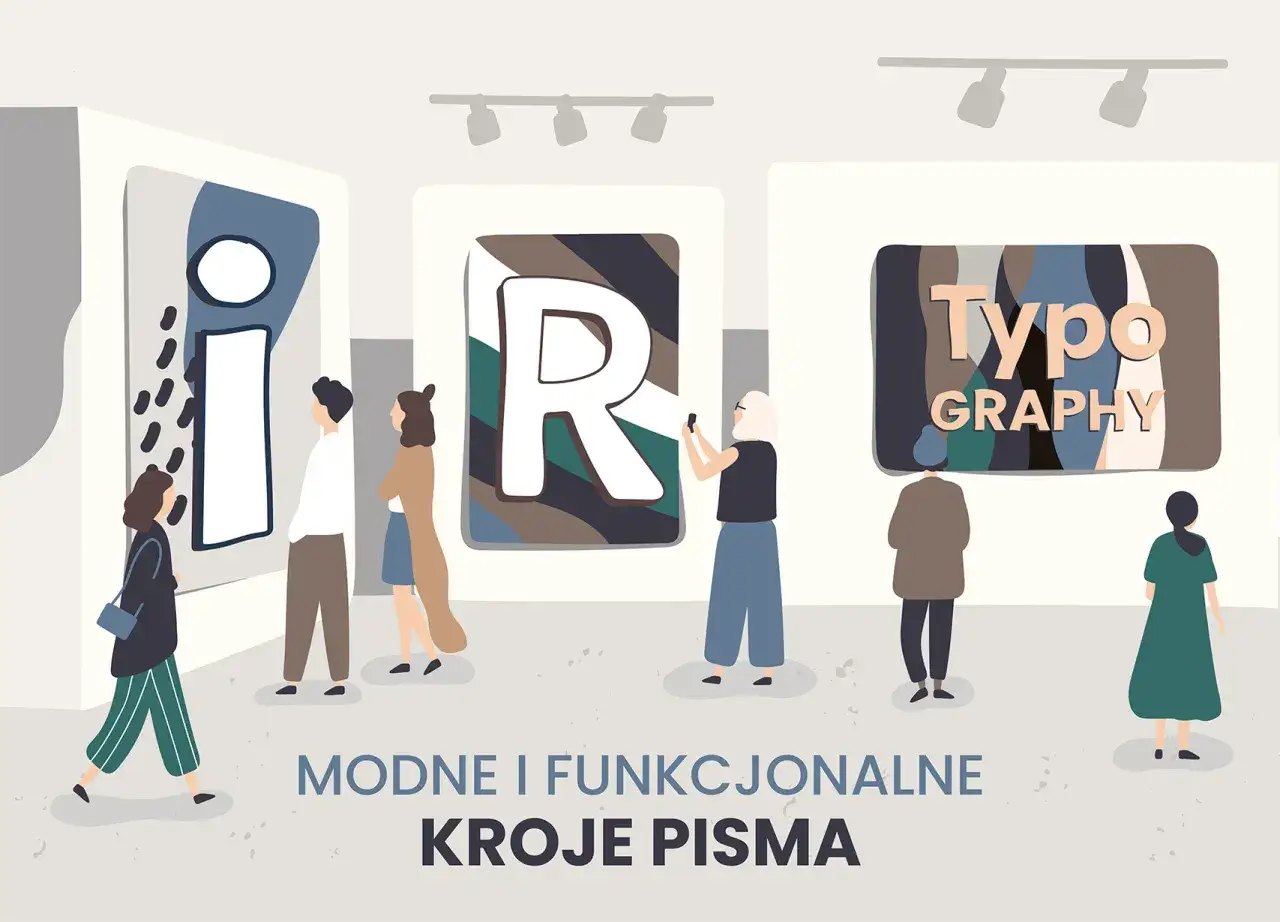
Dziwne czcionki w praktyce. Jak używać ich z wyczuciem
Porównanie zużycia tuszu przez czcionki: Times New Roman, Garamond, Courier, Ryman Eco, bezszeryfowe i szeryfowe. Niektóre dziwne czcionki zużywają mniej tuszu.
Dziwne czcionki potrafią natychmiast nadać projektowi charakter, ale łatwo zamienić ciekawy pomysł w typograficzny chaos. Wyjaśniam, czym różnią się nietypowe kroje pisma od ozdobnych znaków kopiowanych z generatorów, pokazuję ich rodzaje i podpowiadam, jak używać ich w plakatach, logotypach, ilustracjach oraz mediach społecznościowych.
Nietypowy krój działa najlepiej wtedy, gdy wspiera treść
• Eksperymentalne liternictwo może być ozdobą, ilustracją albo głównym tematem kompozycji.
• Jedna wyrazista czcionka zwykle wystarczy, aby nadać projektowi indywidualny styl.
• Znaki Unicode udające fonty nie są prawdziwą czcionką i mogą nie wyświetlać się poprawnie.
• Czytelność ma pierwszeństwo przed efektem, szczególnie w dłuższym tekście i małych rozmiarach.
• Licencja fontu decyduje o tym, czy można użyć go w logo, publikacji albo projekcie komercyjnym.
Wystawa prezentuje nowoczesne, dziwne czcionki i litery, takie jak
Co właściwie kryje się pod określeniem dziwne czcionki
To określenie jest bardzo pojemne. Może oznaczać font z literami przypominającymi bazgroły, krój gotycki, napis złożony z roślin, cyfrowe glitche albo znaki wyglądające jak symbole z obcego alfabetu. W typografii częściej mówi się o krojach ekspresyjnych, dekoracyjnych, eksperymentalnych lub displayowych, czyli przeznaczonych przede wszystkim do krótkich, mocno eksponowanych tekstów.
Trzeba też rozdzielić dwie rzeczy, które w internecie często wrzuca się do jednego worka. Prawdziwy font jest plikiem zawierającym zaprojektowany zestaw znaków, odstępów i reguł ich łączenia. Generator ozdobnych napisów najczęściej podmienia zwykłe litery na znaki Unicode, które tylko przypominają inną czcionkę. Taki napis można wkleić do profilu, ale nie daje on pełnej kontroli typograficznej.
Intencja stojąca za tym tematem jest zwykle mieszana. Część osób szuka szybkiego sposobu na oryginalny nick lub podpis, a część inspiracji do plakatu, tatuażu, okładki czy identyfikacji wizualnej. Dla mnie ta druga grupa jest ciekawsza, bo nietypowe litery najlepiej pokazują swoje możliwości wtedy, gdy stają się elementem obrazu, a nie tylko ozdobą tekstu.
Rodzaje nietypowych krojów i ich charakter
Najłatwiej wybrać odpowiedni styl, gdy najpierw określi się emocję, którą ma wywołać napis. Inaczej działa ciężka fraktura, inaczej delikatne pismo odręczne, a jeszcze inaczej litery celowo zdeformowane przez projektanta.
Rodzaj Jak wygląda Gdzie sprawdza się najlepiej Główne ograniczenie
Blackletter i gotyk Ostre, gęste, historyzujące formy Plakaty koncertowe, okładki, tatuaże, projekty inspirowane średniowieczem Mała czytelność w dłuższych tekstach
Odręczne i brush lettering Nierówne, dynamiczne, przypominające pismo ręczne Zaproszenia, opakowania, plakaty artystyczne, posty lifestyle Trudniejsze dopasowanie liter i polskich znaków
Glitch i dekonstrukcja Przerwane, przesunięte lub „uszkodzone” znaki Muzyka elektroniczna, sztuka cyfrowa, gaming, moda Szybko traci czytelność w małym rozmiarze
Fonty organiczne Litery zbudowane z liści, kości, włókien lub płynnych kształtów Ilustracja, plakaty ekologiczne, fantasy, projekty edukacyjne Najczęściej działają tylko jako pojedynczy napis
Geometryczne i modularne Litery złożone z powtarzalnych modułów Logotypy, infografiki, okładki i identyfikacje marek Potrzebują konsekwentnego systemu odstępów
Ozdobne znaki Unicode Tekst przypominający kursywę, frakturę, bąbelki lub maszynopis Nicki, krótkie bio, podpisy i komunikacja w mediach społecznościowych Różna obsługa znaków na urządzeniach
W praktyce najbardziej efektowne kroje są często najmniej uniwersalne. Font z literą przypominającą pajęczynę może świetnie zadziałać w tytule plakatu, ale po zmniejszeniu do 14 pikseli stanie się plamą. Zawsze testuję napis w docelowym rozmiarze i na docelowym tle, bo podgląd w dużym arkuszu projektowym bywa mylący.
Jak dobrać styl do projektu, a nie tylko do własnego gustu
Najpierw pytam, co odbiorca ma poczuć i zapamiętać. Jeśli projekt dotyczy wystawy o dawnych technikach, gotyk lub krój inspirowany pismem rękopiśmiennym może budować wiarygodny klimat. Przy plakacie o sztuce cyfrowej lepiej sprawdzą się deformacje, pikselowe przerwy albo litery o zmiennym rytmie.
Pomaga prosta zasada funkcji. Tekst informacyjny powinien być spokojniejszy, a nietypowy krój może przejąć rolę nagłówka, podpisu lub znaku rozpoznawczego. Gdy cała strona jest złożona z ozdobnych liter, odbiorca nie wie, co jest najważniejsze i męczy wzrok jeszcze przed przeczytaniem treści.
Trzy pytania przed wyborem fontu
• Czy napis ma być przeczytany w sekundę, czy oglądany jak ilustracja?
• Czy będzie używany tylko raz, czy w całym systemie wizualnym?
• Czy potrzebuję polskich znaków, cyfr, znaków interpunkcyjnych i kilku grubości?
Ostatnie pytanie często przesądza o wyborze. Wiele darmowych fontów wygląda interesująco w alfabecie angielskim, ale nie ma poprawnie zaprojektowanych znaków ą, ć, ę, ł, ń, ó, ś, ź i ż. Zamiast ratować taki krój przypadkowymi zamiennikami, wolę znaleźć font z pełnym zestawem znaków dla języka polskiego.
Gdzie można wykorzystać osobliwe litery
Największy potencjał mają krótkie formy, w których litera może pracować podobnie jak ilustracja. Tytuł wystawy, nazwa serii grafik, okładka zinowego magazynu czy napis na opakowaniu dają projektantowi przestrzeń na eksperyment. W takich realizacjach dopuszczam nawet częściową utratę czytelności, jeśli forma świadomie dopowiada znaczenie.
Plakat i okładka
Na plakacie można rozciągnąć słowo, rozbić je na warstwy, obrócić pojedyncze znaki albo potraktować litery jako fakturę. Dobrym ćwiczeniem jest przygotowanie trzech wersji tego samego hasła: spokojnej, agresywnej i całkowicie abstrakcyjnej. Dopiero porównanie wariantów pokazuje, czy efekt wynika z pomysłu, czy wyłącznie z dekoracyjnego fontu.
Logo i identyfikacja wizualna
W logotypie nietypowa litera może stać się znakiem rozpoznawczym, ale nie powinna utrudniać zapisania nazwy z pamięci. Zanim użyję gotowego kroju, sprawdzam możliwość modyfikacji wybranych znaków, odstępy między literami i wygląd wersji czarno-białej. Logo musi działać zarówno na dużym plakacie, jak i w rozmiarze około 24-32 pikseli w interfejsie cyfrowym.
Media społecznościowe
Do krótkiego bio lub nazwy profilu można użyć znaków Unicode, ponieważ nie wymagają instalowania pliku fontu. To rozwiązanie ma jednak sens głównie dla kilku słów. Przy dłuższych opisach, polskich znakach i ważnych informacjach wybieram zwykły tekst, bo kompatybilność jest ważniejsza od chwilowego efektu.
Liternictwo tworzone ręcznie
Najciekawsze rezultaty często powstają poza biblioteką fontów. Można narysować litery ołówkiem, pędzlem, markerem lub tabletem, a potem zeskanować je i opracować cyfrowo. Taka metoda daje nierówności, których nie da się wiarygodnie udawać gotowym krojem, i pozwala dopasować napis do konkretnej ilustracji.
Prawdziwy font czy ozdobny tekst do skopiowania
Jeżeli potrzebuję jednego krótkiego podpisu w profilu, generator Unicode jest szybki i wygodny. Wpisuję tekst, wybieram wariant, kopiuję go i sprawdzam na telefonie oraz komputerze. Nie traktuję jednak takiego rozwiązania jako zamiennika fontu w programie graficznym.
Kryterium Font zainstalowany w programie Tekst Unicode
Kontrola wyglądu Duża, można zmieniać rozmiar, kerning i układ Ograniczona do dostępnych znaków
Polskie znaki Zależne od zakresu fontu Często problematyczne
Skalowanie Dobre w projekcie wektorowym Zależy od aplikacji i urządzenia
Zastosowanie Druk, logo, grafika, strona internetowa Krótki podpis, nick, bio, wiadomość
Ryzyko Błędna licencja lub brak potrzebnych znaków Puste kwadraty, zastępcze symbole, problemy z czytnikami ekranu
Najczęstszy błąd polega na tym, że ozdobny zapis trafia do nazwy wydarzenia, daty albo adresu. Jeśli część odbiorców zobaczy w tym miejscu kwadraty lub niezrozumiałe symbole, projekt przestaje spełniać swoją funkcję. W przypadku ważnych komunikatów lepiej użyć prawdziwego fontu i dekoracyjny styl ograniczyć do grafiki.
Przy każdym pliku sprawdzam też licencję. Informacja „darmowy” nie zawsze oznacza możliwość użycia w reklamie, logo lub produkcie sprzedawanym komercyjnie. Licencja, zakres znaków i format pliku są równie ważne jak sam wygląd liter.
Jak eksperymentować, żeby nie stracić czytelności
Dobry projekt typograficzny potrzebuje kontrastu. Jeśli nagłówek jest bardzo dekoracyjny, tekst pomocniczy powinien być prosty, najlepiej w kroju bezszeryfowym o regularnym rytmie. Zwykle ograniczam zestaw do jednego fontu ekspresyjnego i jednego neutralnego, a różnicę buduję wielkością, grubością oraz odstępami.
W tekście ciągłym sprawdzają się kroje, w których litery mają wyraźne kształty i równy kolor optyczny. Na ekranie zaczynam od rozmiaru około 16-18 pikseli, interlinii wynoszącej mniej więcej 1,4-1,7 rozmiaru tekstu i długości wiersza około 50-75 znaków. To nie są sztywne prawa, ale dobry punkt wyjścia do testów.
Przeczytaj również: Jak dobrać litery do projektu? Fonty, znaki i czytelność
Typowe błędy początkujących
• Używanie kilku konkurujących ze sobą ozdobnych fontów w jednym projekcie.
• Rozciąganie liter, aby „dopasować” napis do pustego miejsca.
• Ignorowanie polskich znaków i sprawdzanie tylko przykładowego alfabetu.
• Ustawianie zbyt małego kontrastu między tekstem a tłem.
• Brak testu w druku, na telefonie lub w pomniejszonej wersji.
Szczególnie ostrożnie podchodzę do efektów cienia, obrysu i zniekształcenia. Czasem poprawiają charakter napisu, ale częściej maskują słaby krój. Najpierw projektuję czarne litery na jasnym tle, a dopiero potem dodaję kolor, fakturę lub światło. Dzięki temu od razu widać, czy kompozycja działa bez scenografii.
Najciekawsze efekty powstają między fontem a ilustracją
Nietypowe liternictwo nie musi być gotowym zestawem znaków. Można zbudować słowo z przedmiotów, narysować je fragmentami, wyciąć w papierze, odbić z matrycy albo połączyć z fotografią. Takie podejście jest bliskie sztukom wizualnym, ponieważ litera zaczyna funkcjonować jako kształt, rytm, faktura i ślad narzędzia.
Dobrym ćwiczeniem jest wybranie jednego słowa, na przykład „szum”, „cień” albo „organic” i opracowanie go pięcioma metodami. Raz można użyć grubego markera, raz cienkiej stalówki, innym razem wyciąć litery z folii lub stworzyć je z powtarzających się punktów. Nie każda wersja będzie użyteczna, ale każda pokaże, jak forma zmienia odbiór znaczenia.
Właśnie dlatego nie oceniam osobliwego fontu wyłącznie po tym, czy wygląda efektownie w katalogu. Liczy się relacja między literą, słowem i miejscem użycia. Najlepszy wybór czasem nie jest najbardziej „dziwny”, tylko ten, który pozostawia odbiorcy odrobinę zaskoczenia i nadal pozwala mu bez wysiłku odczytać komunikat.
Mały test przed publikacją oszczędza dużo pracy
Przed oddaniem projektu robię krótki test w czterech wersjach. Sprawdzam napis w dużym rozmiarze, w pomniejszeniu, w skali szarości i bez efektów specjalnych. Jeśli nadal rozpoznaję słowo, polskie znaki nie odstają, a kompozycja zachowuje hierarchię, font prawdopodobnie spełnia swoje zadanie.
Na końcu pytam jeszcze, czy odbiorca potrzebuje informacji, czy doświadczenia wizualnego. Przy instrukcji, podpisie dzieła albo danych wydarzenia wybieram klarowność. Przy plakacie artystycznym, okładce lub eksperymentalnej ilustracji pozwalam literom być bardziej niepokornym, ale zawsze robię to z konkretnym powodem, a nie dla samego efektu.
Najbardziej udane nietypowe kroje nie konkurują z treścią. Wydobywają jej ton, epokę, energię albo materiałowość. Gdy potraktujesz litery jak część kompozycji, a nie przypadkową dekorację, nawet bardzo osobliwy napis może stać się czytelny, charakterystyczny i naprawdę artystyczny.
FAQ - Najczęstsze pytania
Font jest plikiem z zaprojektowanym zestawem znaków, odstępami i regułami ich łączenia, dlatego można używać go w programach graficznych, druku i projektach wektorowych. Tekst Unicode tylko zastępuje litery podobnymi znakami, więc sprawdza się głównie w krótkim nicku, bio lub podpisie. Na różnych urządzeniach może wyświetlać puste kwadraty, mieć problemy z polskimi znakami i utrudniać pracę czytnikom ekranu.
Najpierw określ, jaką emocję ma wywołać napis i czy odbiorca ma go szybko przeczytać, czy oglądać jak ilustrację. Gotyk pasuje między innymi do plakatów koncertowych i projektów historyzujących, glitch do sztuki cyfrowej i gamingu, a organiczne litery do ilustracji oraz projektów ekologicznych. W tekście informacyjnym użyj spokojniejszego kroju, a dekoracyjny ogranicz do nagłówka, podpisu lub znaku rozpoznawczego.
Sprawdź obecność znaków ą, ć, ę, ł, ń, ó, ś, ź i ż, a także cyfr, interpunkcji oraz potrzebnych grubości. Wiele darmowych fontów wygląda dobrze w alfabecie angielskim, ale nie ma kompletnego polskiego zestawu znaków. Przed użyciem w logo, reklamie lub produkcie komercyjnym sprawdź również licencję, format pliku i zakres dozwolonych zastosowań.
Sprawdź napis w docelowym rozmiarze i na docelowym tle, a następnie przygotuj wersję dużą, pomniejszoną, czarno-białą i pozbawioną efektów specjalnych. Dla tekstu ciągłego dobrym punktem wyjścia jest rozmiar 16-18 pikseli, interlinia 1,4-1,7 oraz długość wiersza około 50-75 znaków. Logo powinno zachować czytelność także w rozmiarze około 24-32 pikseli.